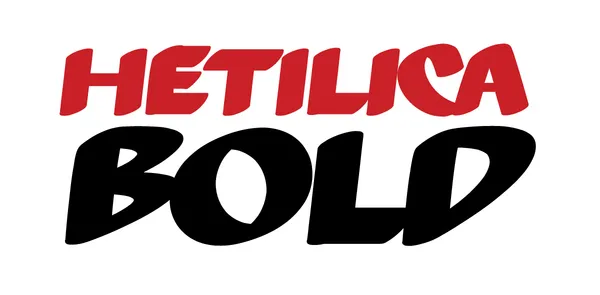
A Hetilica Font é uma seleção rara e divertida para quem busca algo que se destaca no ambiente digital dos anos 80 e 90. Desenvolvida como um projeto final para a nossa turma de workshop em 2009, a fonte Hetilica Bold carrega na sua essência aquele ar retrô nostálgico que tanto faz vibrar as memórias de uma geração. Hamilton é o autor desta bela fonte, cada traço e linha aqui preservando esse toque vintage que torna esta fonte especialmente atraente para projetos de design retro ou clássicos. Em um mundo em constante evolução, a Hetilica Font oferece uma paleta de texturas únicas capaz de transformar qualquer layout, seja ele num site pessoal ou em um aplicativo de redes sociais. Ideal tanto para aqueles que querem transportar o público para um tempo mais antigo quanto para quem aprecia a beleza simplória e assertiva dos anos passados, a Hetilica Font é uma escolha inteligente para qualquer designer que procura expressar suas ideias de forma única e memorável.